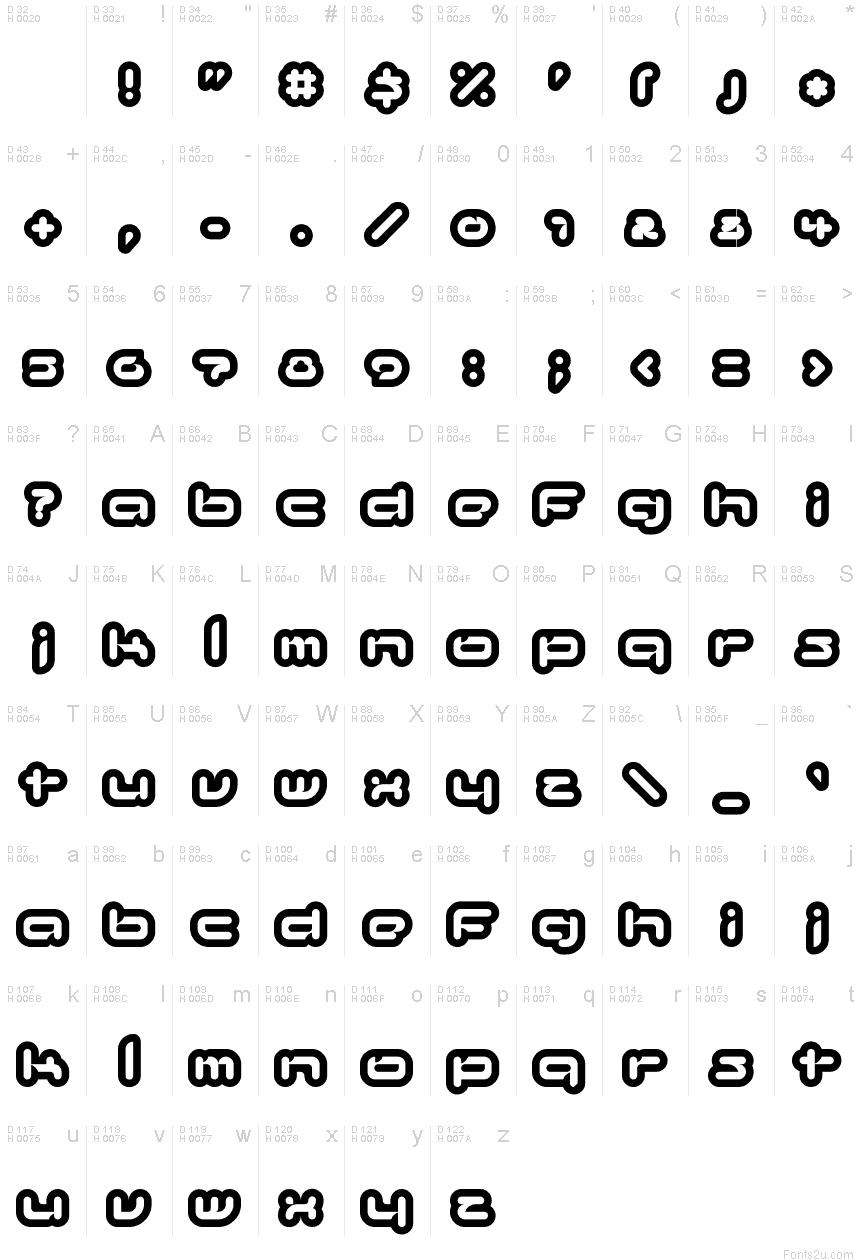
Kinkimono autorstwa Koena Hachmanga to darmowy, futurystyczny krój typu display o odważnym, rurowym rytmie, który sprawia wrażenie zarówno zabawnego, jak i mechanicznego. Każda litera wygina się niczym neonowa rurka, tworząc masywne, zaokrąglone narożniki oraz wąskie, niemal labiryntowe prześwity. Ciężkie zewnętrzne linie i otwarte wnętrza tworzą wyrazistą sylwetkę, która mimo to zachowuje wizualną lekkość.
Dzięki Kinkimono nagłówki zyskują natychmiast niezapomniany klimat retro-sci-fi i „toy-tech”. Ten darmowy font świetnie sprawdzi się na plakatach, okładkach albumów, w tytułach gier, brandingu wydarzeń, eksperymentalnych logotypach oraz przykuwających uwagę grafikach do mediów społecznościowych. Stosuj duże rozmiary, aby wijące się kształty pozostały czytelne, a w mniejszych formatach łącz go z prostym, geometrycznym bezszeryfem, aby pozwolić tym nietuzinkowym konturom grać główną rolę.